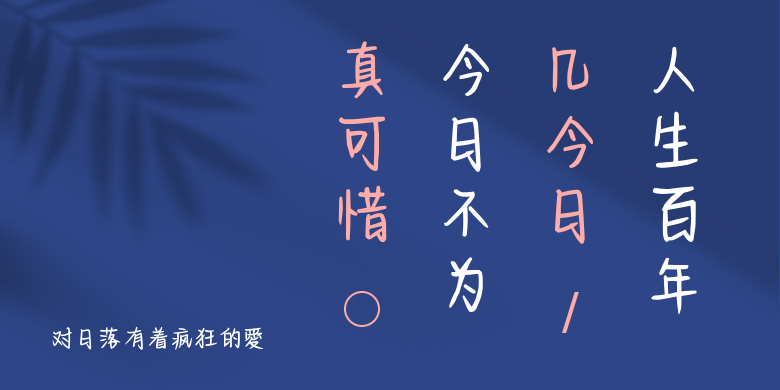
对日落有着疯狂的愛
对日落有着疯狂的愛,这款字体结构工整、笔画清晰,兼顾美观与易读性,适用于标题、正文、海报、包装、LOGO 等多种场景。字形优雅稳定,风格百搭耐看,适配日常排版与创意设计,让文字呈现更舒适、更具质感。对日落有着疯狂的愛一笔一画,皆是细节,以均衡的比例、流畅的线条打造舒适视觉体验,字形端正大气,风格简约现代。无论是商业设计、品牌宣传还是日常排版,都能轻松驾驭,让文字更有格调与力量。对日落有着疯狂的愛字体下载。